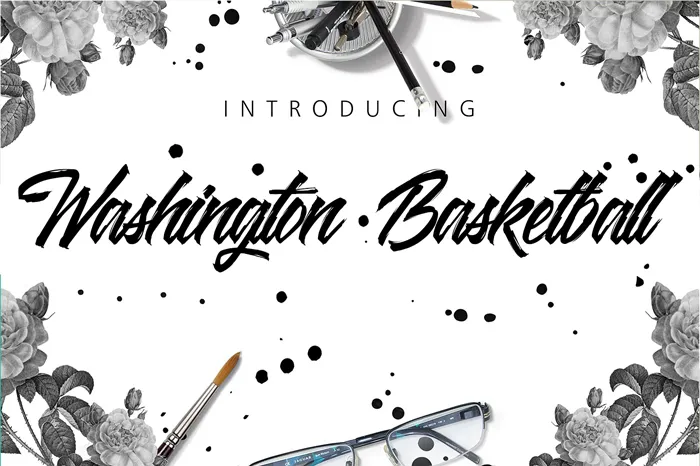
Washington Basketball Font – Download Grátis
A fonte Washington Basketball é uma tipografia à mão livre criada para aqueles que buscam elegância na sua designação visual. Embora esteja inspirado no estilo do basket nacional, a sua natureza sofisticada e harmoniosa faz dela uma escolha perfeita para o estilista de logomarcas que busca dar um toque especial às suas criações. Sujeito a qualquer aplicação, seja ela um logotipo elegante, convites memoráveis, embalagens de produto minimalistas ou até mesmo cartões de felicitações cuidadosamente escritos e coloridos, Washington Basketball garante uma sensação de elegância e sofisticação que torna sua presença notável. Com seu uso inteligente na composição visual, a fonte Washington Basketball pode fazer qualquer arte digital ganhar um toque definitivamente diferenciado. A Octotype lançou esta font como uma opção de Brush Fonts para aqueles buscando um gás especial em seus projetos visuais, e é o tipo de escolha que torna seu trabalho ainda mais atraente e memorável.